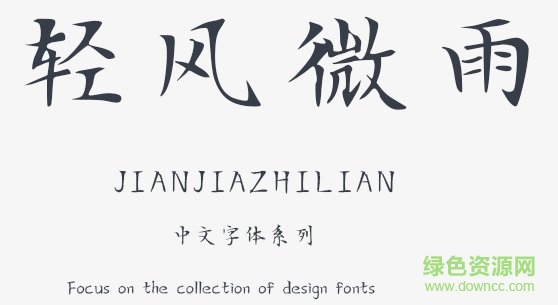
輕風(fēng)微雨字體是一款具有楷書特色的手寫字體,筆觸細(xì)膩而軟硬兼具,具有古風(fēng)字體韻味的特色魅力,給藝術(shù)設(shè)計(jì)增添獨(dú)特魅力,綠色資源網(wǎng)獨(dú)家推薦!
輕風(fēng)微雨ttf字體是一款形象飽滿、結(jié)構(gòu)勻稱的中文字體,字庫(kù)完整,可以滿足設(shè)計(jì)師們的工作需要,字跡清新而端莊,有著極佳的閱讀好感。